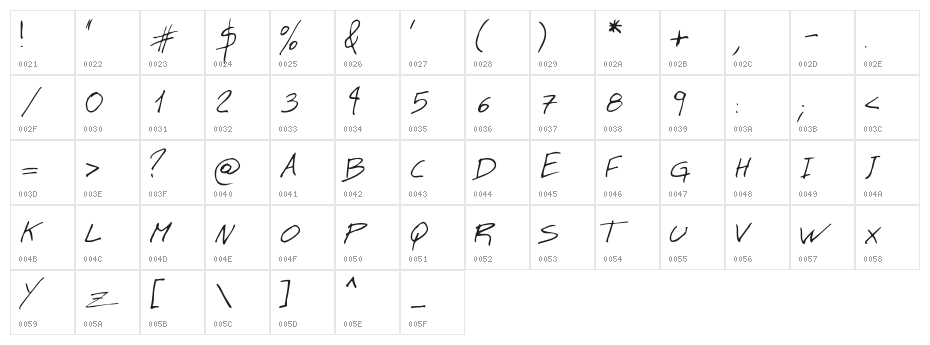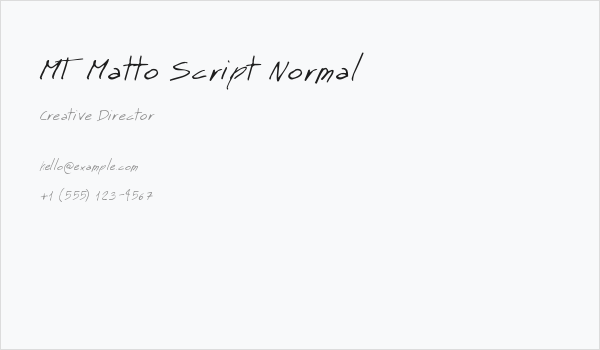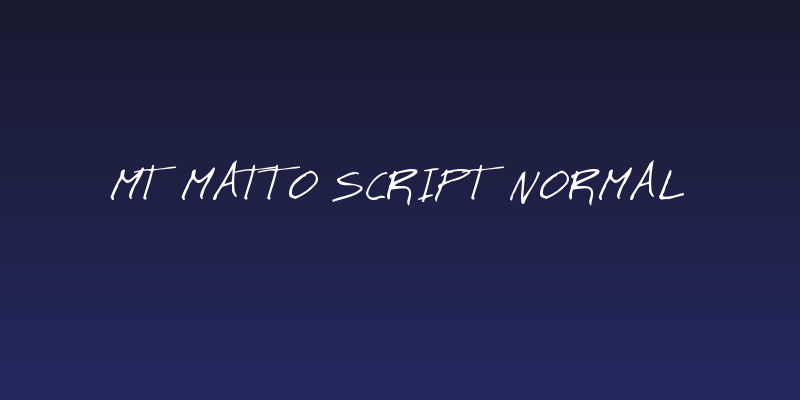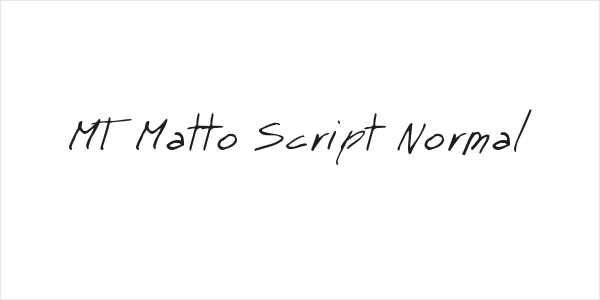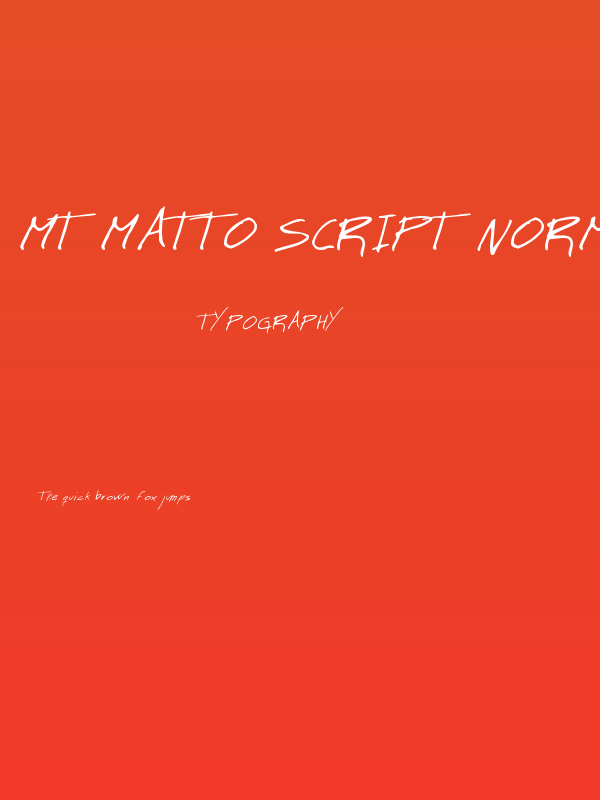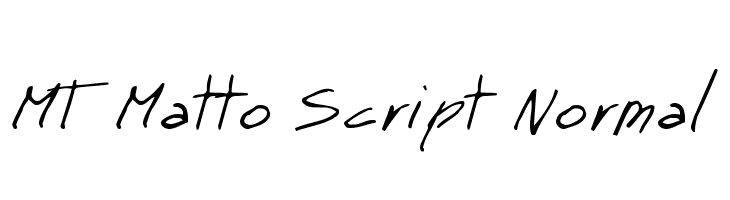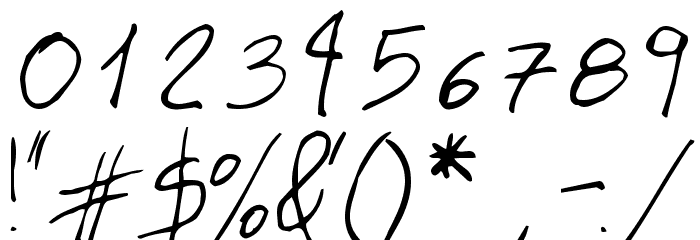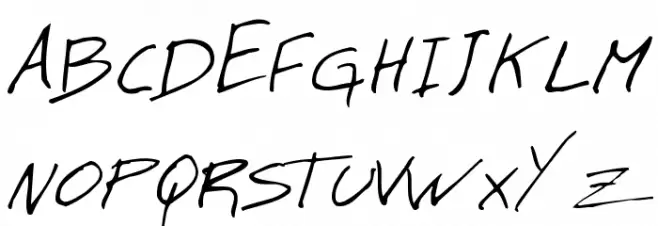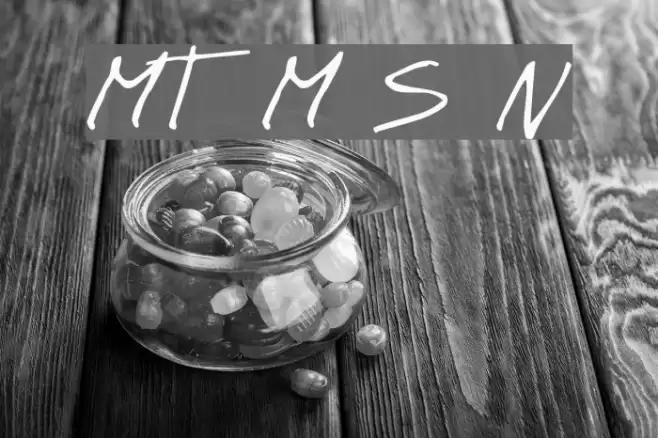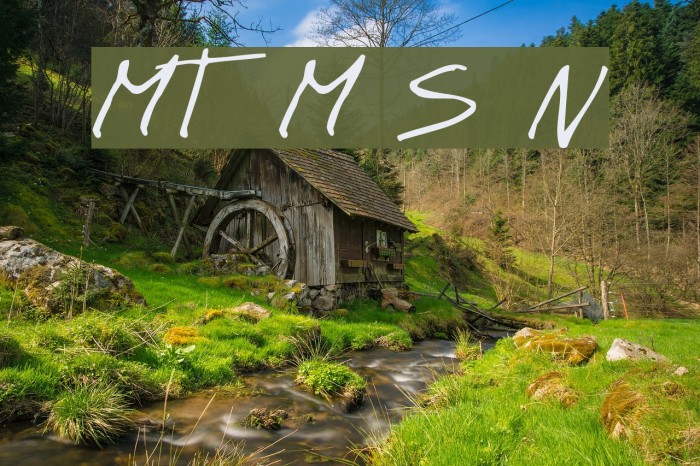
MT Matto Script Normal Font
| Anwendungsfall | Logos, Invitations, Personal Branding |
| Vorgeschlagene Projekte | Ideal for greeting cards, invitations, personal branding, and creative projects that require a personal, handwritten touch. |